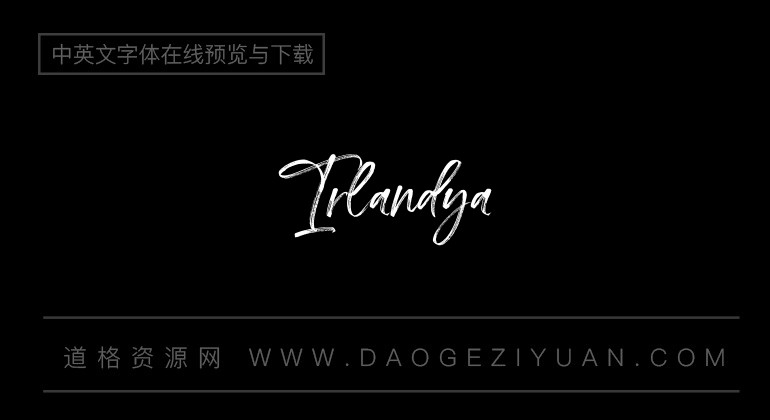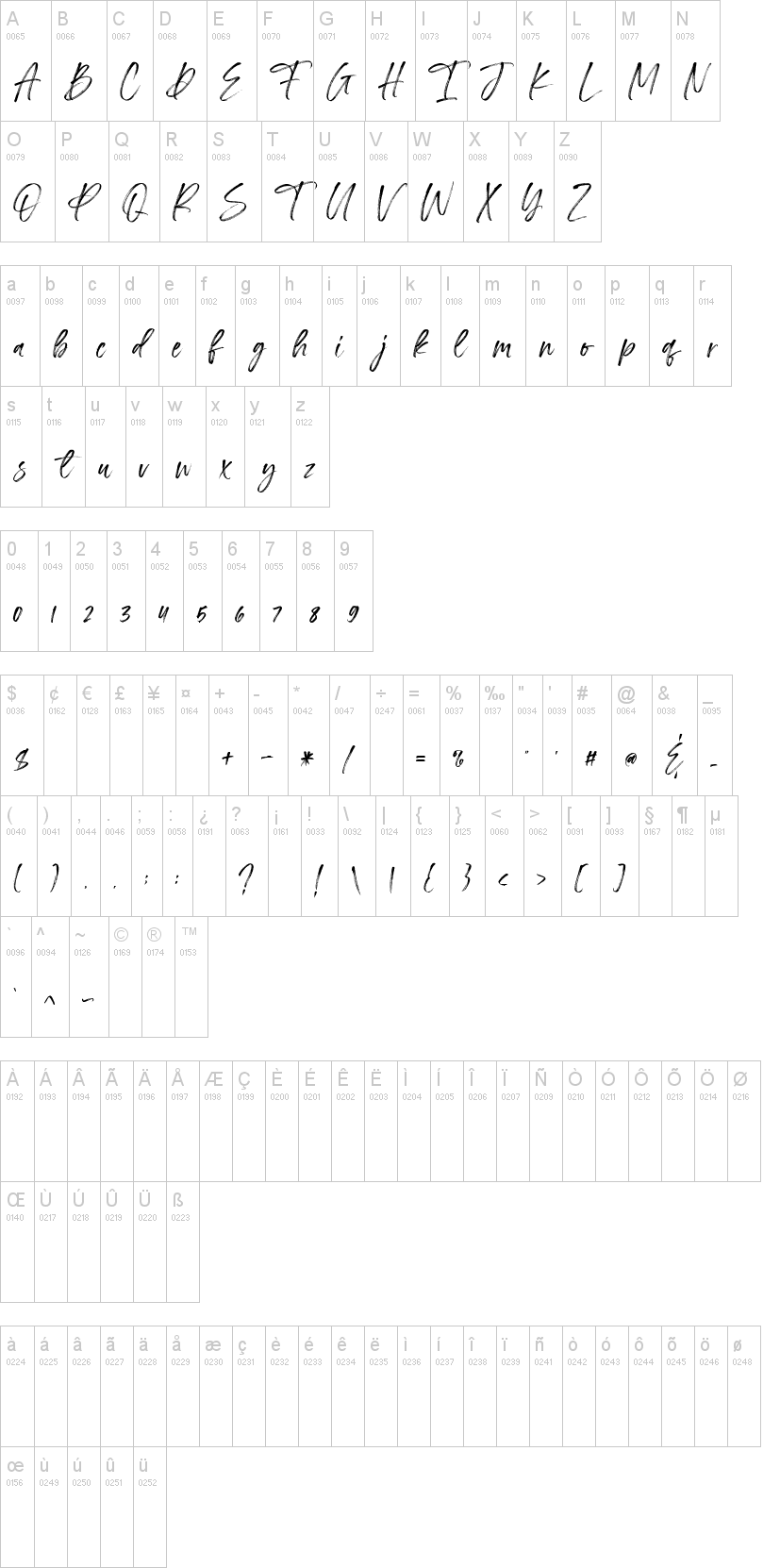
Irlandya
Irlandya 字体是一款具有爱尔兰特色的英文字体,由著名设计师米歇尔·贝尔曼(Michelle Belmont)设计。字体灵感来源于爱尔兰的文化和传统,具有传统的英文字体风格,但又具有独特的爱尔兰特色。字体设计简洁大方,清晰易读,适合用于印刷和网络文档,也可以用于标志和标语设计。
Irlandya是一款非常不错的手写艺术字体,具有很好的视觉感,适合于文化类的宣传设计、商业类品牌的广告和产品包装设计以及个性化文字排版等较多场景。
Irlandya字符映射图